29 种植物灵感设计的最佳花卉字体
已发表: 2022-03-30想为您的设计增添一丝女性优雅吗? 花卉字体是做到这一点的好方法。
无论您是为您的企业创建品牌元素的花店,还是寻找完美邀请函字体的婚礼策划师,花卉字体都是提升您的设计并赋予它们更多视觉趣味的好方法。
然而,有时很难在网上找到漂亮的花卉字体。
在本文中,我们将列出 29 种在线可用的最佳花卉字体,以帮助您为您的植物设计找到完美的花卉主题字体。
但首先,让我们了解更多关于花卉字体的定义。
什么是花卉字体?
花卉字体是包含与花卉、树木、树叶和任何其他类型的植物生命相关的元素的字体。 一些花卉字体的花朵与字母交织在一起,而另一些则有计数器(a、b、d、e、g、o、p 和 q 内的空间),形状像你最喜欢的花卉图案。
花卉字体非常适合为您的设计提供更优雅和自然的感觉,而且它们也可以非常通用。 它们在 T 恤、海报、邀请函上看起来很棒,甚至可以作为以自然为中心的企业的品牌字体。
29 种植物设计的最佳花卉字体
如果您一直在寻找完美的花卉主题字体,那就别无所求。 这是在线提供的 29 种最佳花卉字体的最终列表,从我们的首选开始。
1.花卉字体——我们的首选
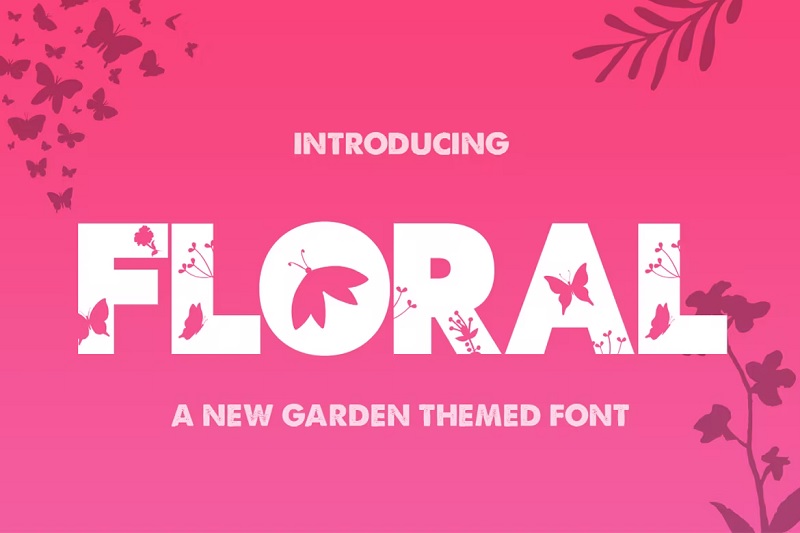
花卉字体正是顾名思义,是击败所有其他字体的花卉字体。 这种令人惊叹的字体是大胆的、少女的,而且真的很漂亮。 这种字体有蝴蝶形状的计数器,以及贯穿始终的花卉轮廓。
为什么它是我们的首选
这种字体大胆而美丽,适用于各种设计。 无论您是制作时尚服装还是节日海报,这种字体一定会吸引路人的注意。
2. Candreeva 花卉字体
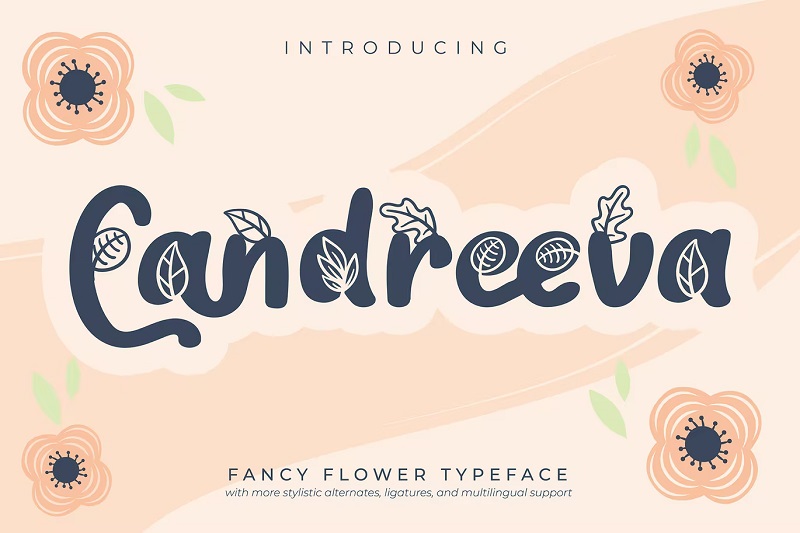
Candreeeva 是一种书法风格的花卉字体,在商品和海报上看起来很棒。 该字体大胆、有趣且非常可爱,并且贯穿始终包括叶子和花朵的设计。 除了大写和小写字符外,字体包还包括大量字形、替代字和连字。
3. Verdant Flower 字体
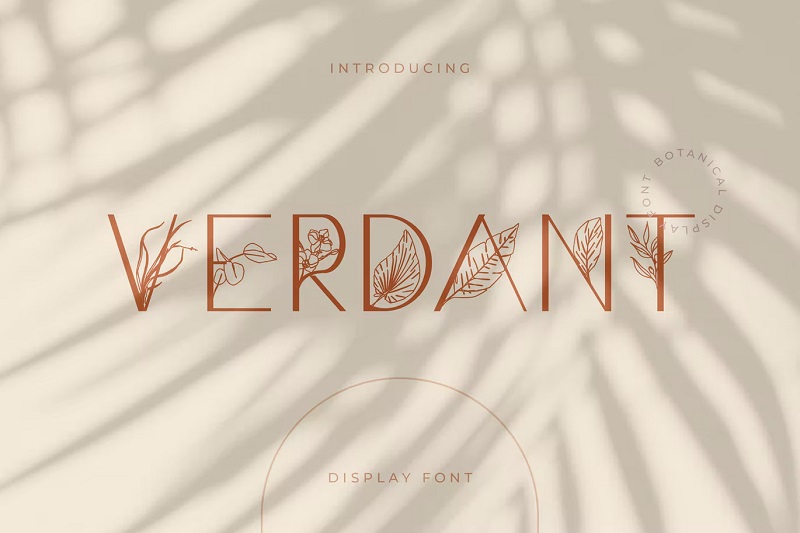
Verdant 是一种优雅而精致的花卉字体。 这种字体非常适合为夏季婚礼制作优雅的邀请函,甚至可以在名片和花卉企业的标牌上制作。 这种字体与常规衬线和无衬线字体完美搭配,如果您想为您的设计添加一些精致的花卉装饰,也是一个不错的选择。
4.不要担心手绘字体
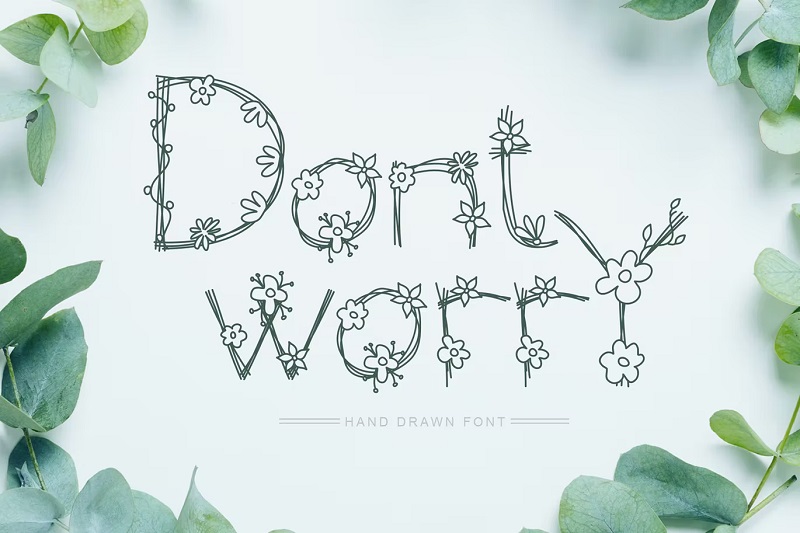
Don't Worry 是一种真正独特的字体,非常适合波西米亚风格的设计。 这种不拘一格的字体由交织在一起的树枝、雏菊和樱花组成。 对于环保企业来说,这将是完美的品牌字体,而且在杯子和文具等个性化商品上看起来也很棒。
5. Satine Floral Display字体
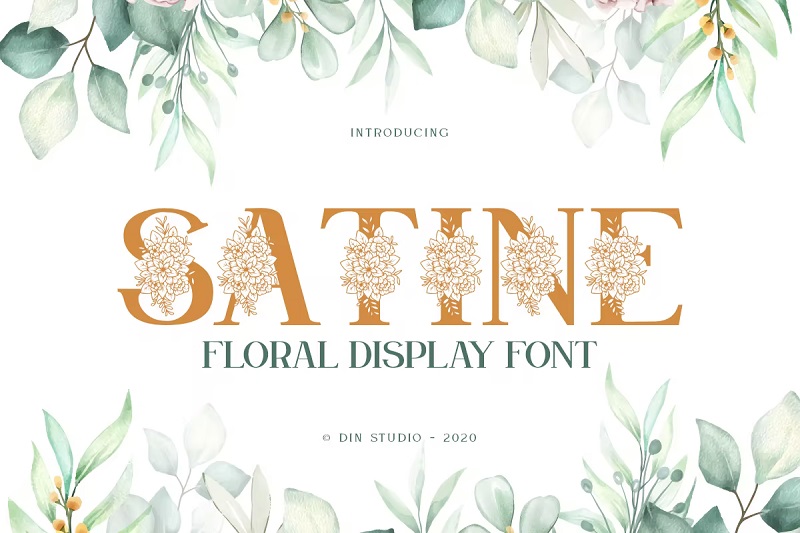
Satine 是一种高度装饰性的花卉展示字体,非常适合婚礼和其他特殊场合。 这种字体中的每个字母都装饰着美丽的花朵,它一定会为您的设计增添一丝优雅和优雅。 这种字体甚至可以很好地用作社交媒体帖子和其他数字内容的字体。
6. Bintari 显示字体
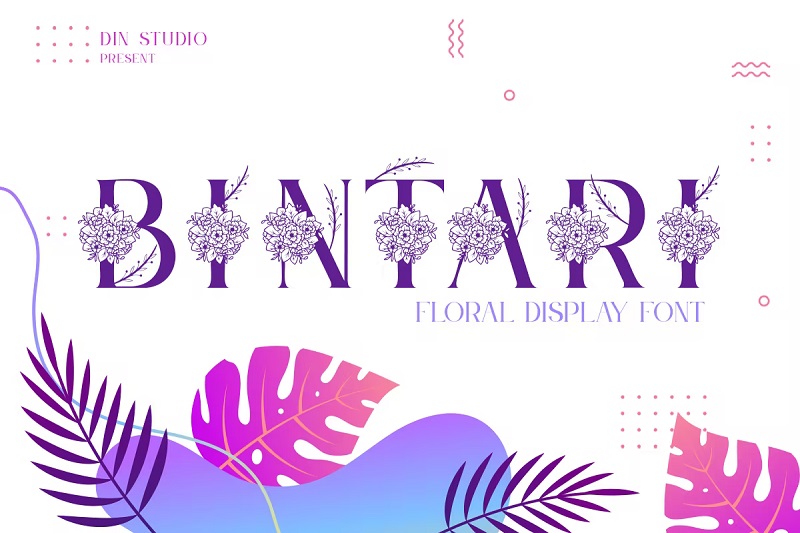
Bintari 是另一种极其奢华的显示字体,带有花卉元素。 这种优雅的字体包括树叶小枝和颓废的花卉元素,一定会给你的设计带来奢华的感觉。 这种字体非常适合贺卡和文具,以及字母组合项目。
7. Arleafia 装饰字体
Arlefia 是一种带有叶子设计的细而装饰性的线条字体。 每个字母都包含高度装饰性的叶子,有助于为您的设计带来自然、环保的感觉。 这种字体非常适合引用设计,并且在商店、餐馆和咖啡馆的标牌上看起来也很棒。
8. Flora Delicate Floral 字体
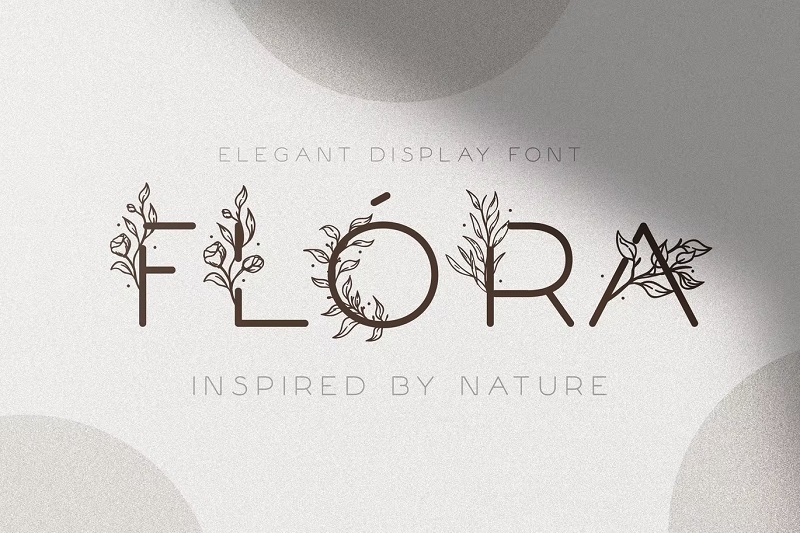
Flora 是一种窄而精致的展示字体,融合了美丽的花朵和优雅的叶子。 这种优雅的字体真的很独特,在婚礼请柬和活动海报上看起来都很完美。 尽管具有高度的装饰性和女性气质,但该字体仍然非常易于阅读,这对于装饰性显示字体来说总是一个好处。
9.弹簧字体
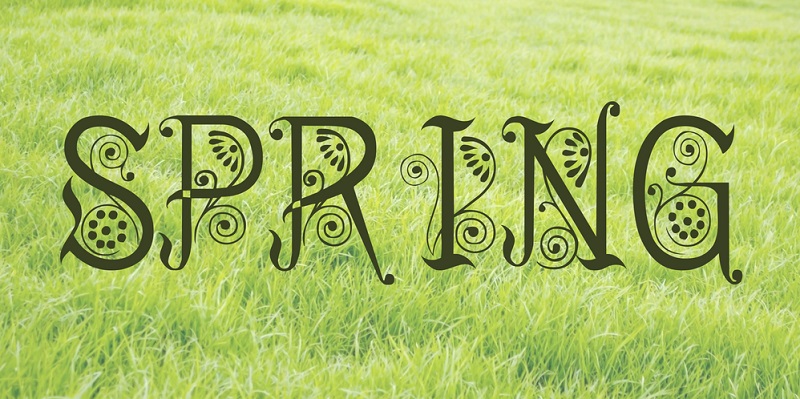
春天是一种令人愉快的花卉字体,带有怀旧的感觉。 它让人想起文艺复兴时期异想天开的老式设计。 这种字体在时期主题活动的海报和标牌上看起来很棒。 字体下载包括 52 个字母和字符。 但是,它不包括数字集。
10.花园浪漫字体
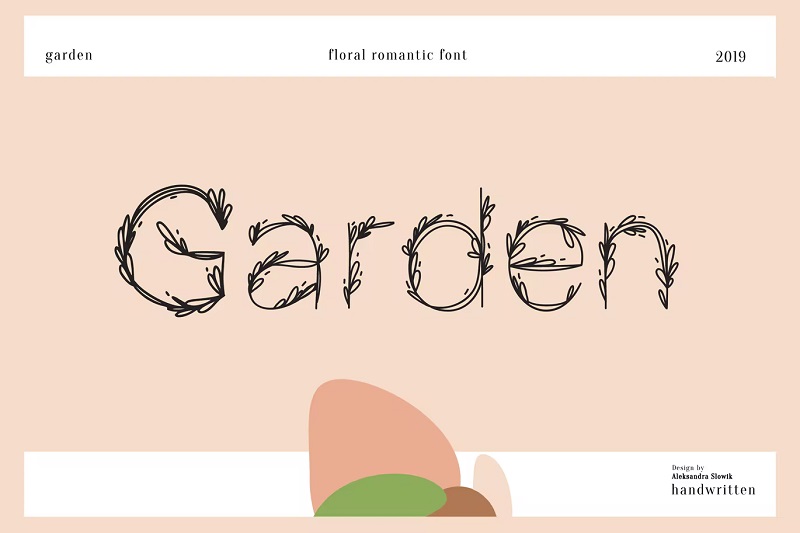
Garden Romantic 是一种低调的花卉字体,采用绿叶设计。 这些字母让人想起交织在一起的藤蔓,它们还包括精致的叶子元素。 这种字体在带有字母组合的物品上看起来很棒,也可以用于海报和其他类型的标牌。
11. Everbloom花卉字体
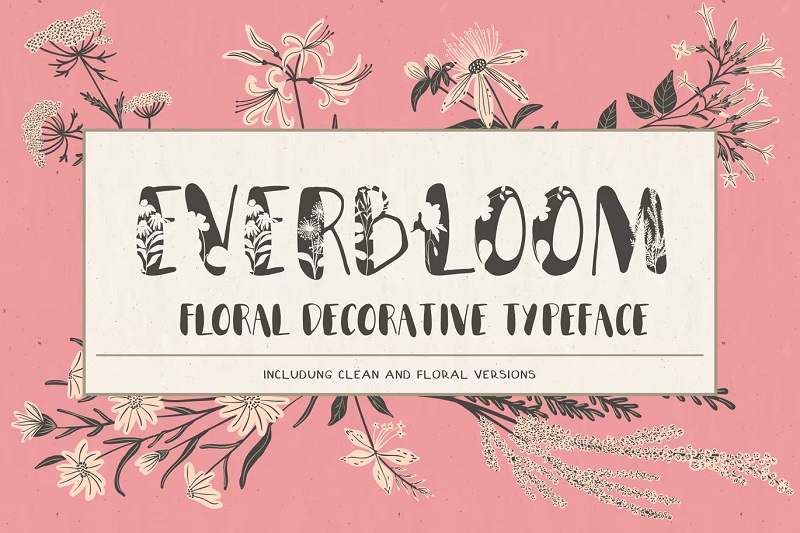
Everbloom 是一种古怪而曲线美的花卉字体,非常适合做出大胆的声明。 字体包包括两个版本的字体,一个带有装饰花卉图案,还有一个干净的手绘版本。 您可以同时使用这两个版本的字体来创建美观且有凝聚力的设计。
12. Snowy Winter Floral 字体
Snowy 是冬季活动的完美花卉字体。 大胆的块状字体包括雪花图案和冬青枝,营造出斯堪的纳维亚风格的圣诞氛围。 该字体将是节日贺卡、圣诞集市海报的完美选择,而且在豪华礼品袋上看起来也很棒。
13. Bahor 手工字体
Bahor 是一种全大写的手工花卉字体,非常适合字母组合。 大胆而优雅的字体饰有精致美丽的手绘花朵。 字体包包括两个不同版本的字母表,带有不同的花卉图案,因此您可以混合搭配它们以创建独特而精致的设计。
14. Wonder Floral 字体
Wonder 是一款优雅的花卉字体组合,具有波西米亚风格。 该二重奏包括两种字体,两种字体都装饰有独特而复杂的花朵和叶子图案。 不仅如此,这个花卉字体包还包括匹配的数字和标点符号。
15. KR花卉脚本字体
KR 是具有复古感觉的花卉脚本。 字体让人联想到 60 年代的花朵力量,每个字母都采用风格化的雏菊设计。 KR 花卉脚本全部大写,并配有匹配的感叹号、问号,还包括数字。
16. Hello Wild 字体
Hello Wild 是一种有趣而古怪的花卉字体,带有热带风情。 这些字母以独特的书法风格绘制,包括风格化的叶子和花朵,它们似乎是从字母本身生长出来的。 这种字体在贺卡、海报上看起来很棒,也可以作为社交媒体字体使用。
17. Vignellya 花式花字体
Vignellya 是一种具有花哨感觉的书法风格字体。 优雅而弯曲的字体在派对邀请函、T 恤以及商店或餐厅的招牌上看起来很棒。 除了漂亮的大写字母外,Vignellya 还包含一系列字形、连字和替代字形。
18. Gabriella Flower 字体
Gabriella 是一种有趣且乐观的花卉字体,非常适合作为可爱、以儿童为中心的设计的一部分。 精美的手绘字母点缀着从顶部探出的可爱花朵。 除了小写和大写字母外,字体包还包括字形、替代和连字。
19.花卉手绘显示字体
Flower 是一种手绘显示字体,非常适合希望在设计中添加一些大胆的花卉元素的人。 这种超厚实的字体刚刚跳出页面,还充满了可爱的花朵和叶子图案。 这种字体印在商品以及包、杯子和衬衫等服装上看起来很棒。
20.佛罗里达花卉字体
Florida 是一种有趣的花卉字体,具有非常自然的感觉。 使用这种字体,叶子、小枝和花瓣会从每个字母中弹出,它一定会给您的设计带来真正的植物感。 字体包还包括连字、替代字和大量字形。